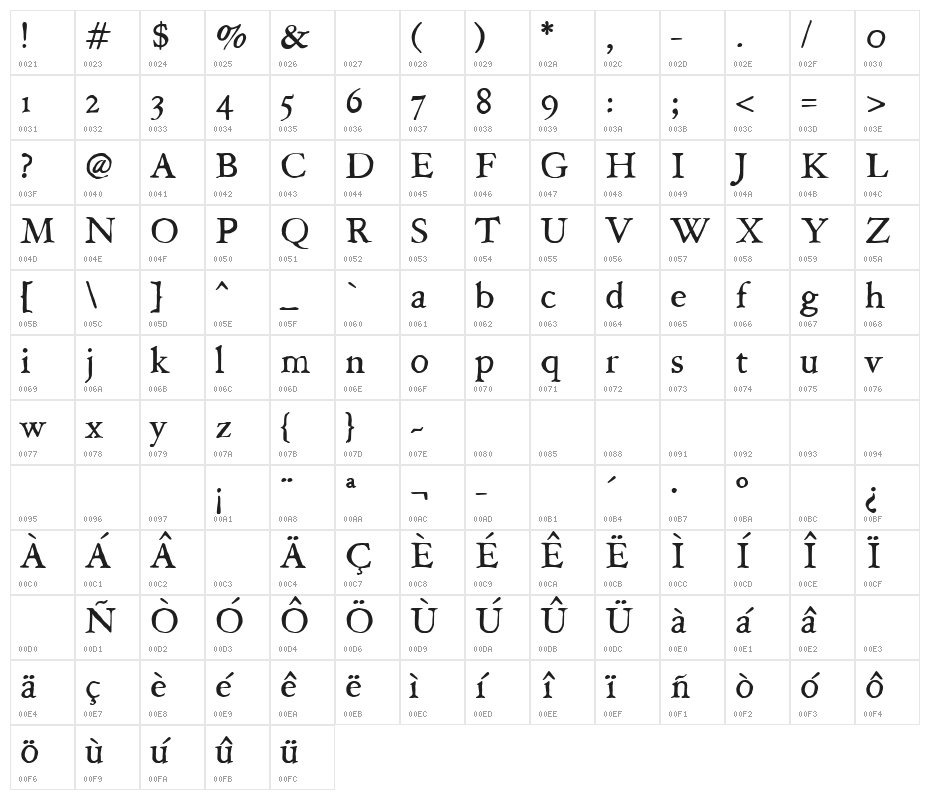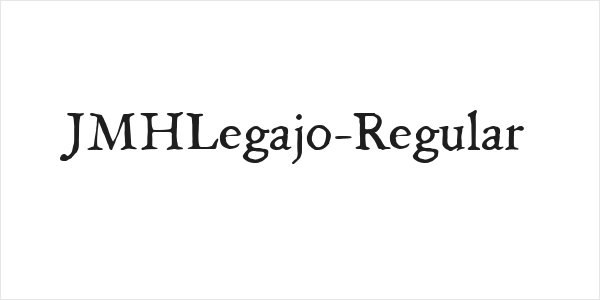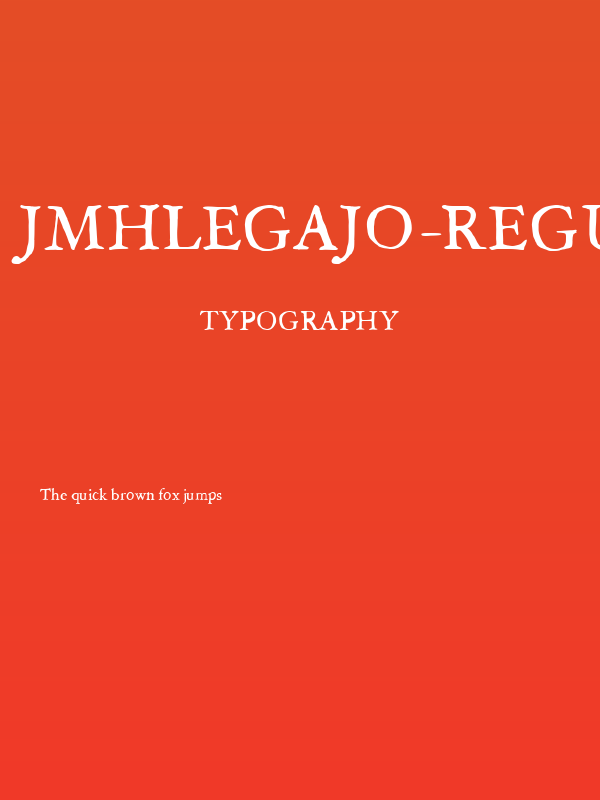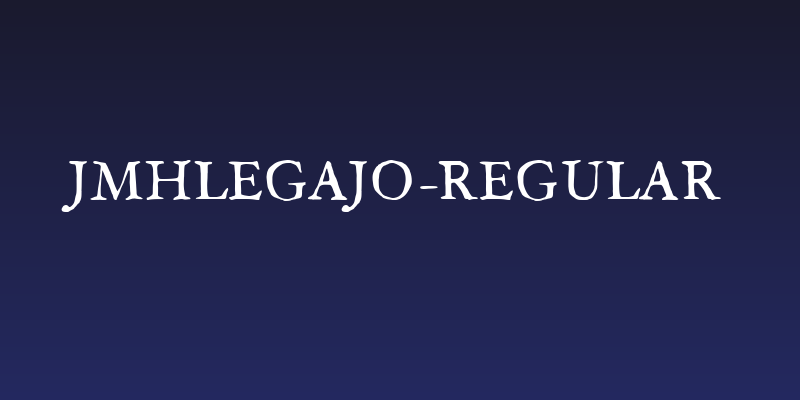
JMHLegajo-Regular Font
| Estilo general | Vintage |
| Caso de uso | Logos, Invitations, Artistic projects |
| Proyectos propuestos | Ideal for projects requiring a historical or artistic touch, such as invitations, certificates, branding for artisanal products, or book covers. |